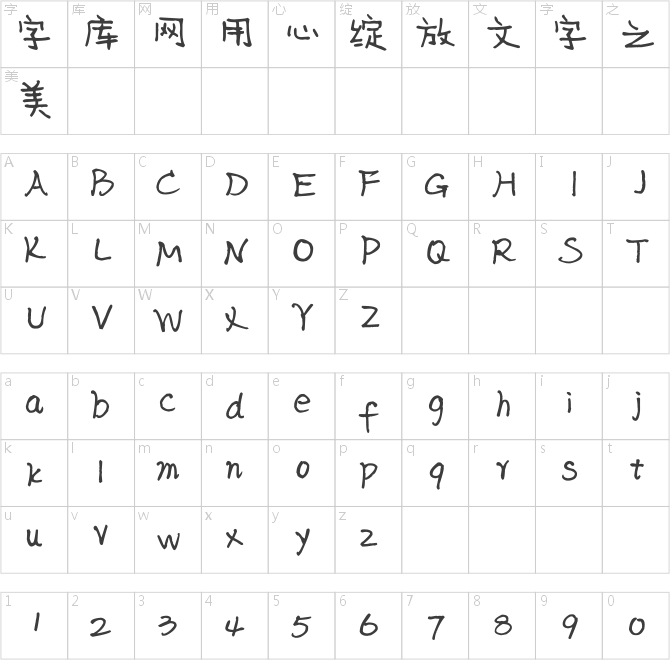
字体名称: 陈继世神韵晓雯
神韵晓雯体字体是一款由神韵字库设计师陈继世打造的艺术字体,该字体将笔画夸张,笔画与笔画采用非常规处理,结构歪斜,重心不稳,使人产生青涩、萌动的感觉,能够适用于艺术设计、包装印刷、签名设计、图形设计等应用。(本字体为个人非商用版,如需要商用请联系作者购买版权)
陈继世神韵晓雯体字体字库是一款让人赏心悦目、百看不厌的中文字体,适合各类广告和产品包装设计应用,字体大小2.33MB,格式为ttf字体,上传用户是神韵,作者/版权方为神韵字库